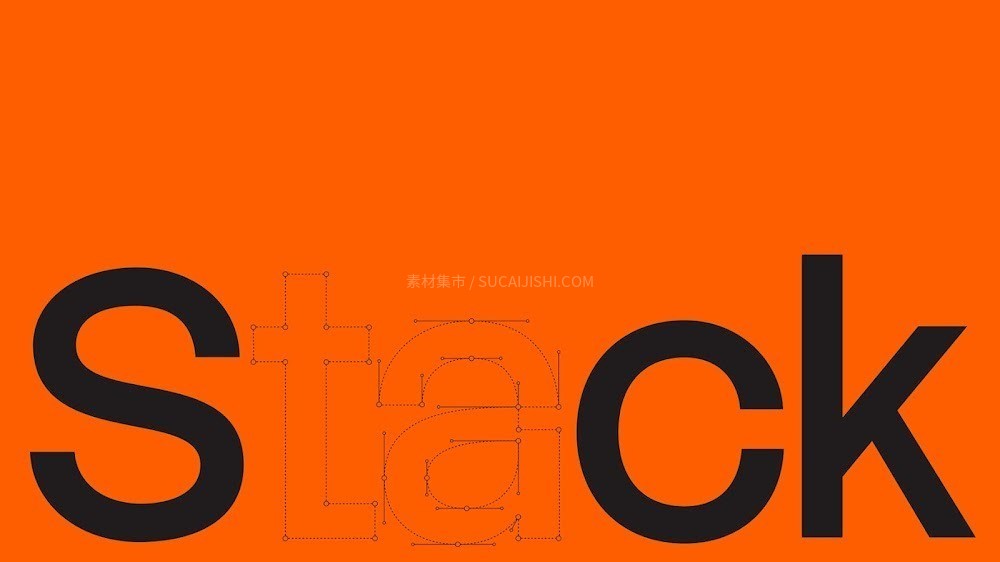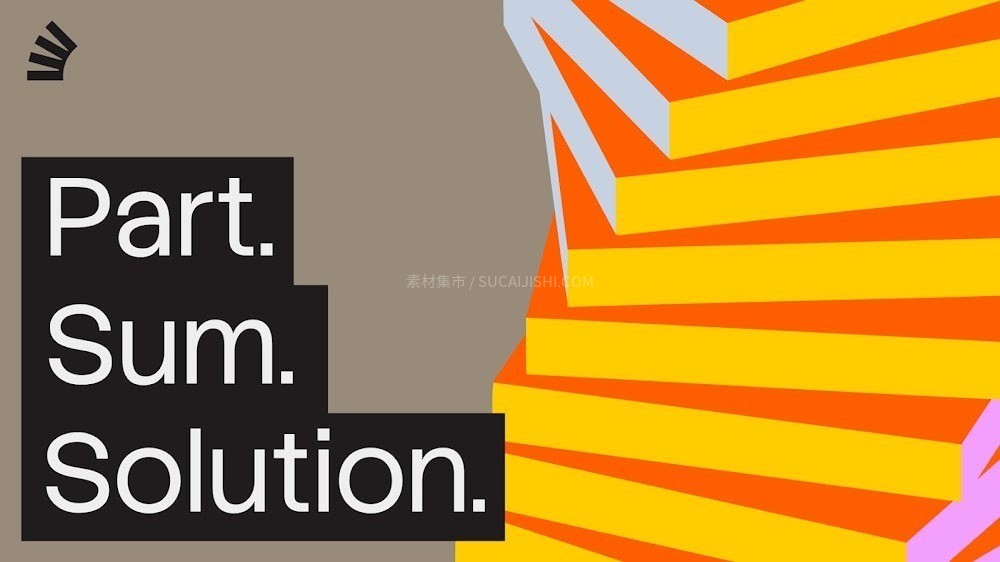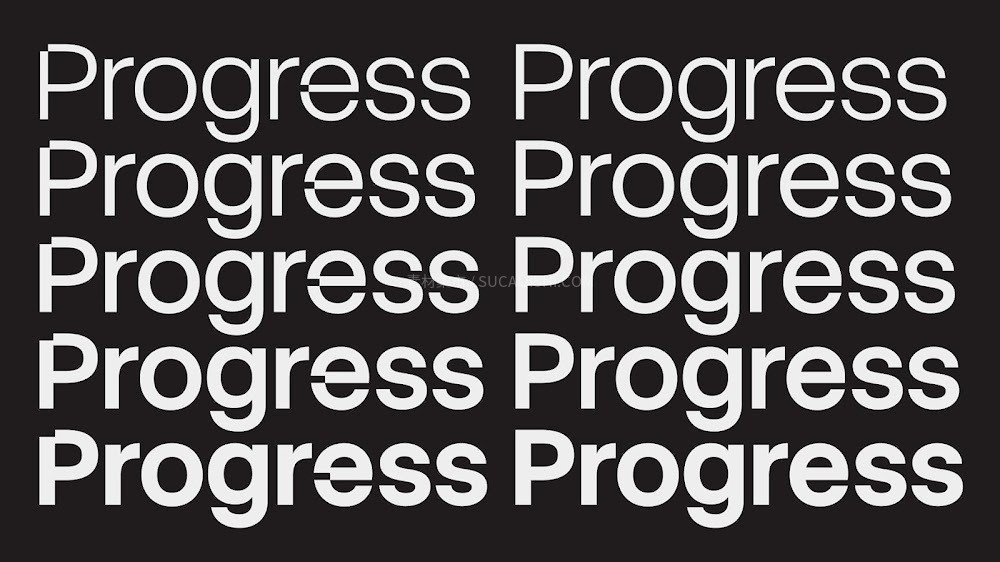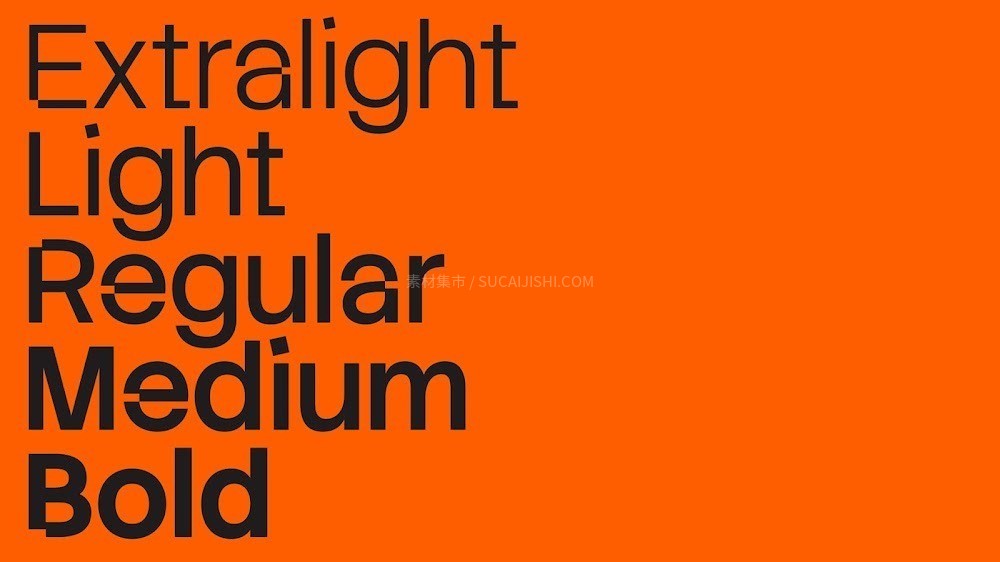
Stack Sans:StackOverflow 开源免费字体
一款超棒的开源免费字体——Stack Sans!这是顶级设计机构 Koto 为全球最大开发者社区 StackOverflow 量身打造的专属定制字体,也是他们品牌重塑的核心元素。这款字体完美打破了传统技术品牌“冰冷、机械”的刻板印象,在严谨的技术逻辑和温暖的社区氛围之间找到了绝佳平衡。字形上融合了利落的线条与人性化的圆角,看起来既专业理智,又超级亲切友善。它还非常细心地划分了两个方向:Display(标题)系列充满视觉张力,非常适合营销宣传和大标题;Text(正文)系列则对高密度排版、代码片段和各种屏幕 UI 界面的阅读体验进行了深度优化,保证了极高的清晰度。